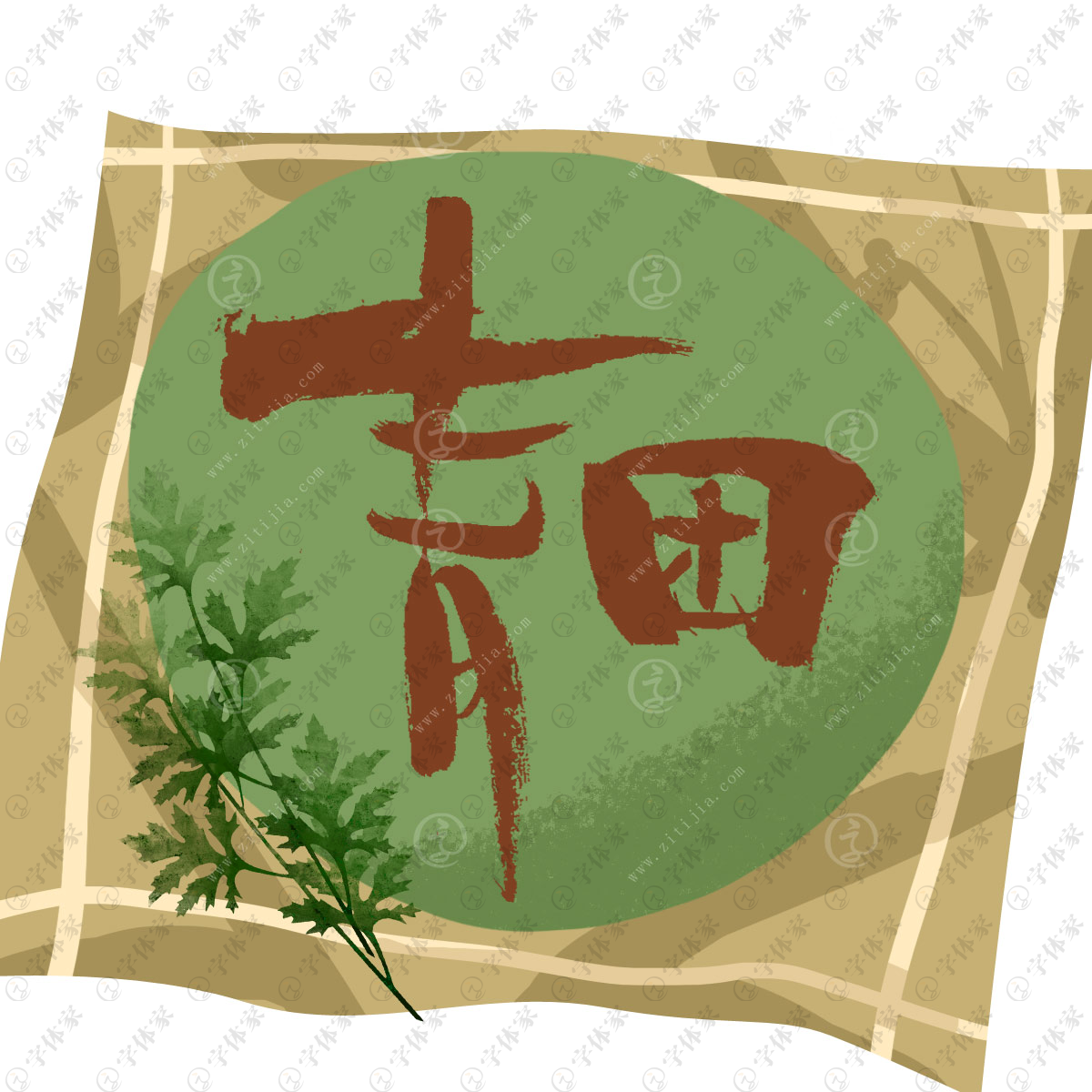
青团是江南地区的传统特色小吃,青色,用艾草的汁拌进糯米粉里,再包裹进豆沙馅儿或者莲蓉,不甜不腻,带有清淡却悠长的清香。青团是江南人家在清明节吃的一道传统点心,据考证青团之称大约始于唐代已有1000多年的历史,每逢清明几乎都要蒸青团,古时候人们做青团主要用作祭祀,虽然青团流传千百年,外形一直没有变化,但它作为祭祀品的功能已日益淡化,而是成了一道时令性很强的小吃。